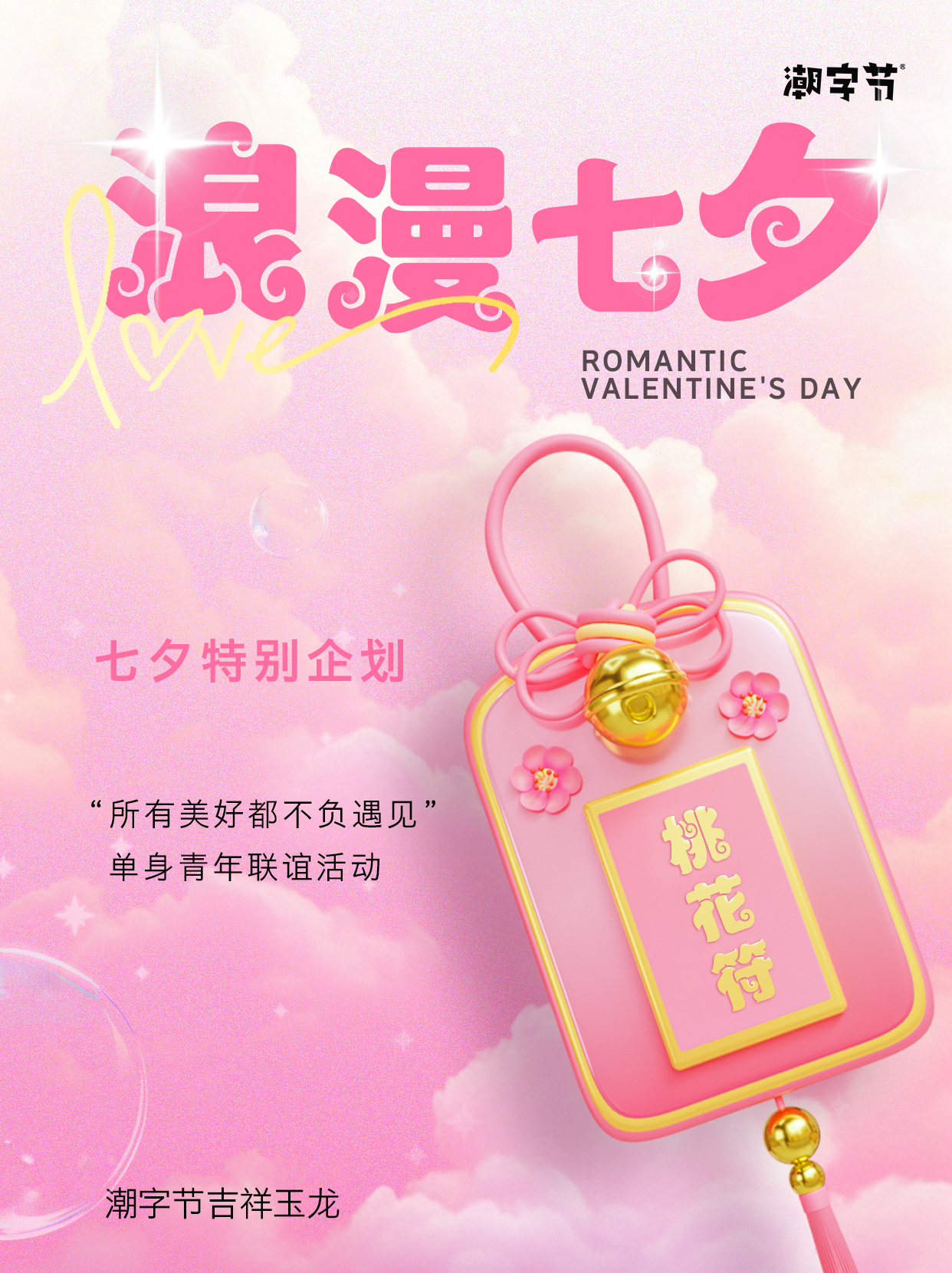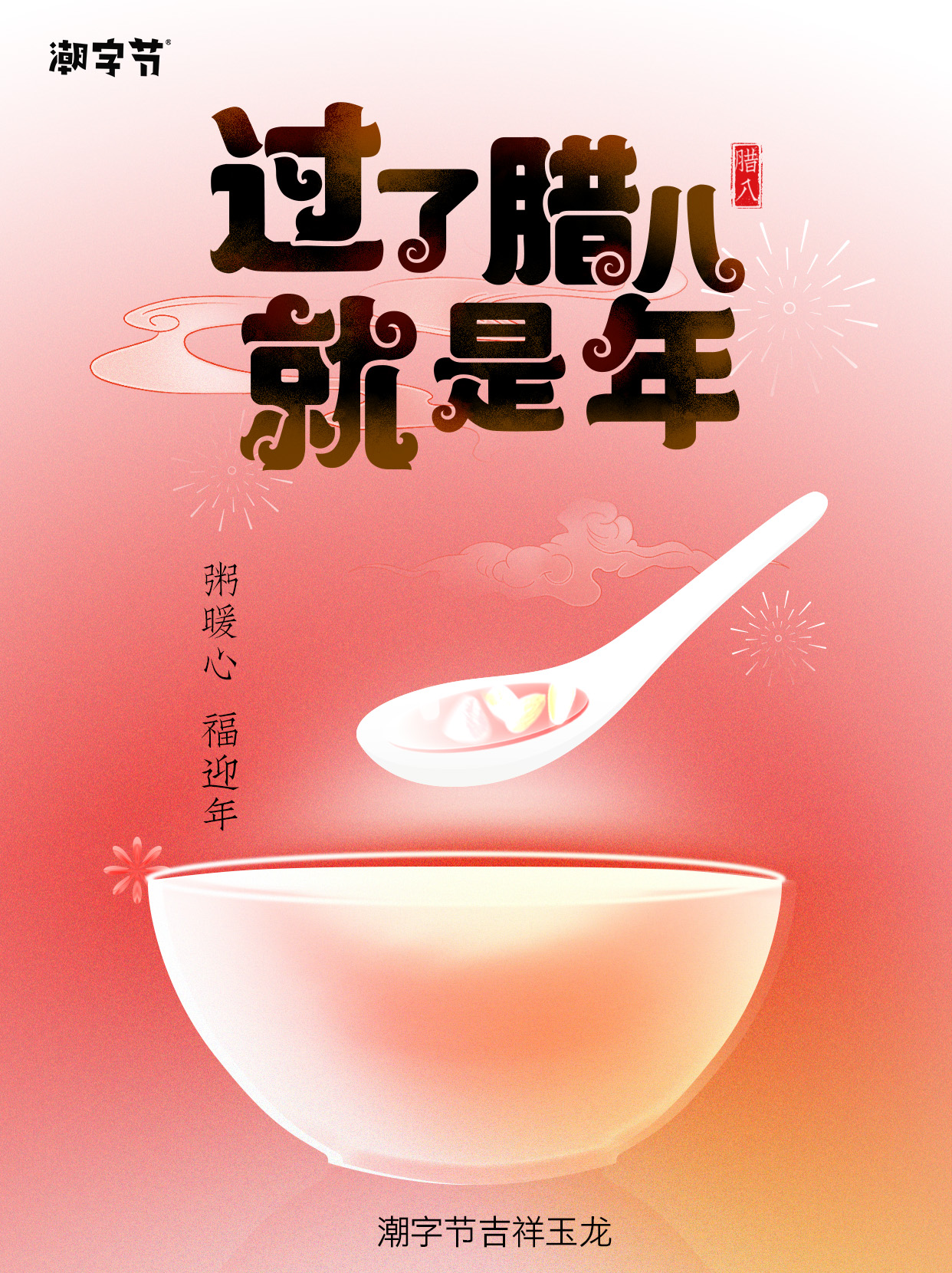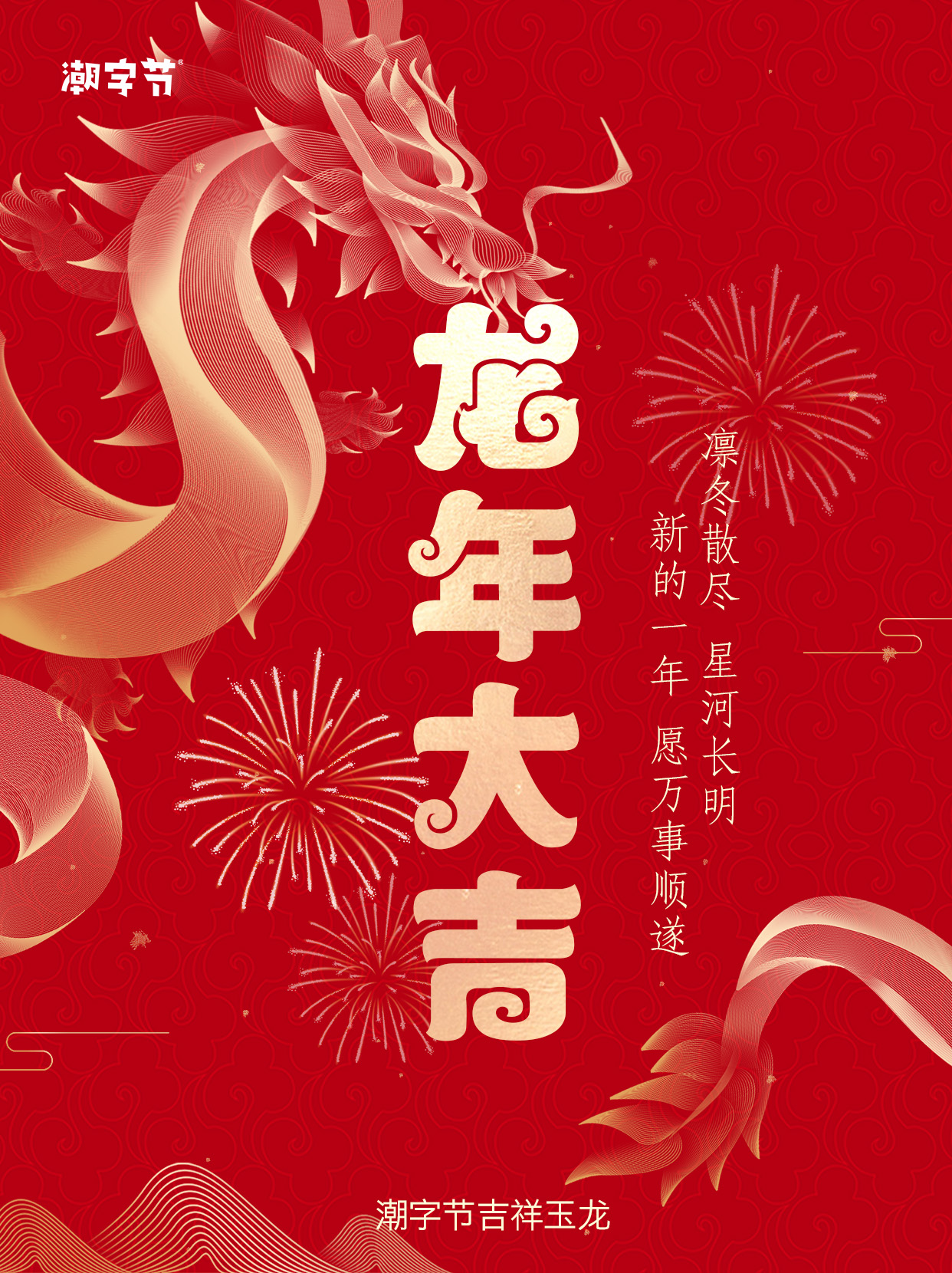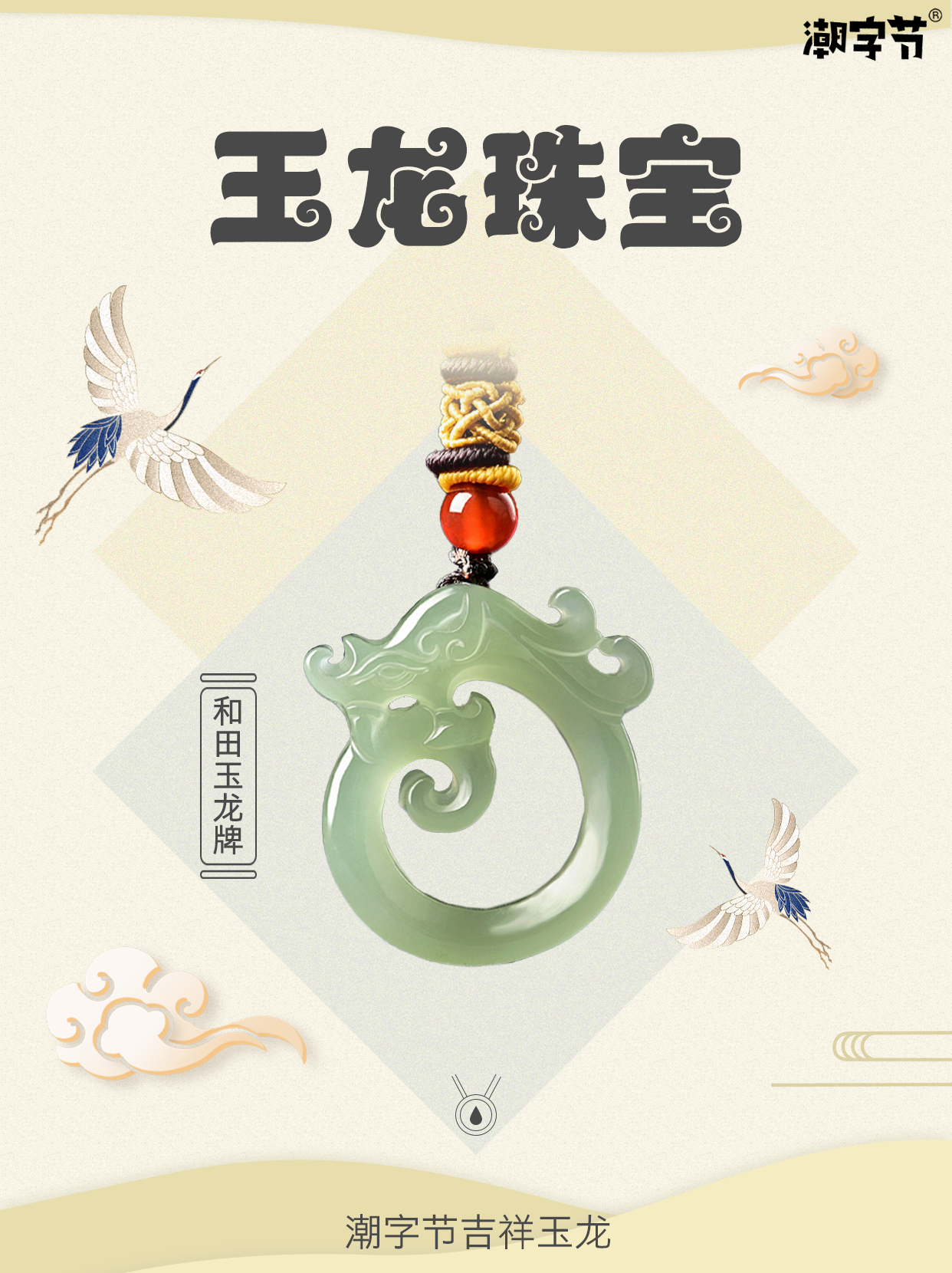
潮字节吉祥玉龙便是以红山玉龙为灵感,借鉴其勾曲线的外形,融入优雅的装饰线,创造性赋予笔画间飞腾的动感当两者相遇结合,即能够相互匹配,又达到了相得益彰的效果。整体造型活泼、别致、优美,而其清晰稳重的结构,辅以自由无束的潮牌元素,用新时代的特质,诠释着中国独有的文化符号。从标题、正文、宣传语到品牌的标准用字等需求。